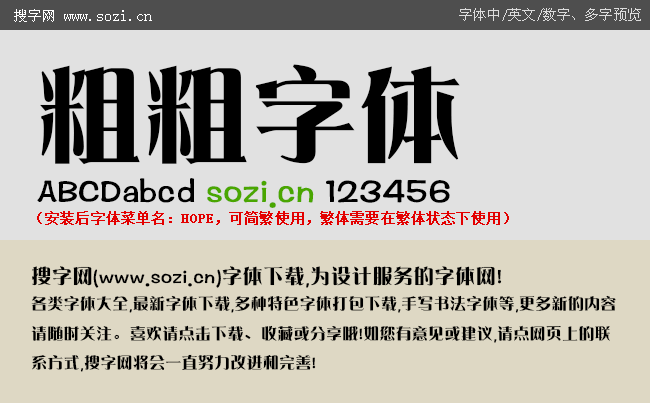
粗粗字體
搜字網(wǎng)給大家提供一款粗粗字體手機(jī)中文字體下載。這款手機(jī)字體是以華康雅宋體為原形,華康雅宋體以宋體的基礎(chǔ)上加以美化,筆畫處修以花邊,轉(zhuǎn)折處稍微圓潤(rùn),相比棱角分明的宋體,又多了一分可親近的感覺。適合喜歡手機(jī)字體個(gè)性一些的朋友在手機(jī)上安裝使用。